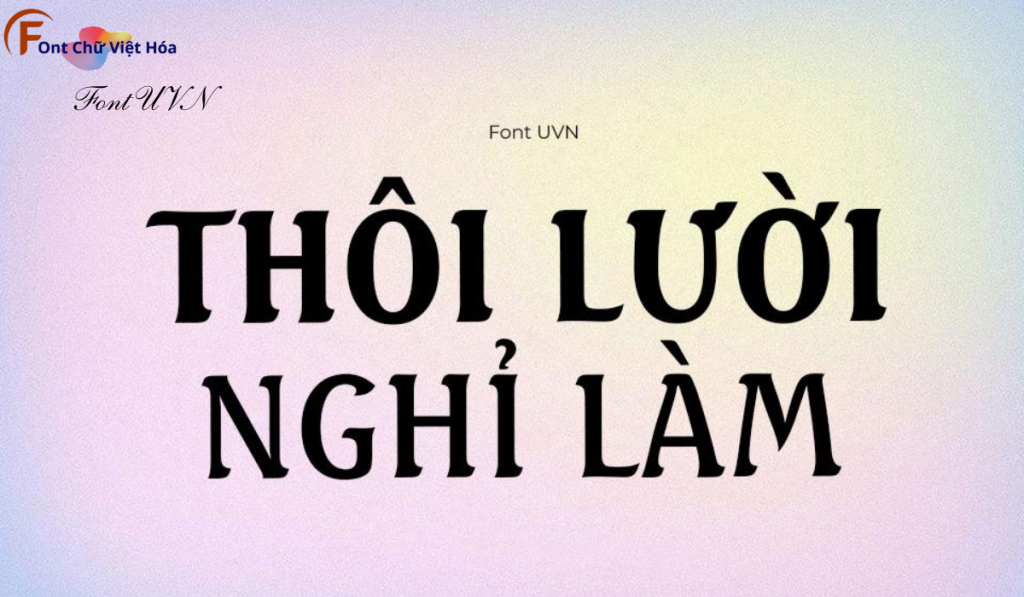
Font UVN Chim Biển Việt Hóa
Tác giả: UVN Chim Biển Việt Hóa
Bộ Font: UVN
Phân loại: Cá tính, Độc đáo
Kiểu chữ: Có chân
Độ dày: Thường
Font UVN Chim Biển Việt Hóa là một font chữ có chân cá tính, thuộc bộ font UVN. Được thiết kế với mục tiêu mang lại sự độc đáo và sáng tạo, font này lý tưởng cho các dự án thiết kế như logo, poster, và bao bì sản phẩm. Với các nét chữ sắc nét và độ dày đều đặn, Font UVN Chim Biển Việt Hóa không chỉ dễ đọc mà còn tạo cảm giác hiện đại và phá cách.